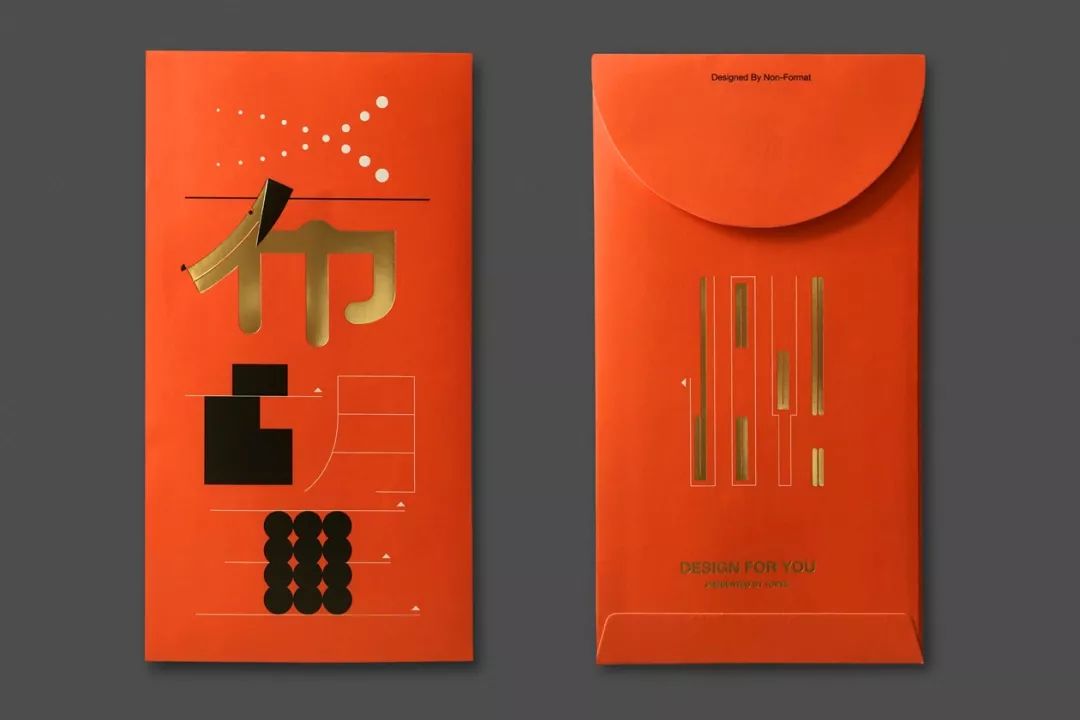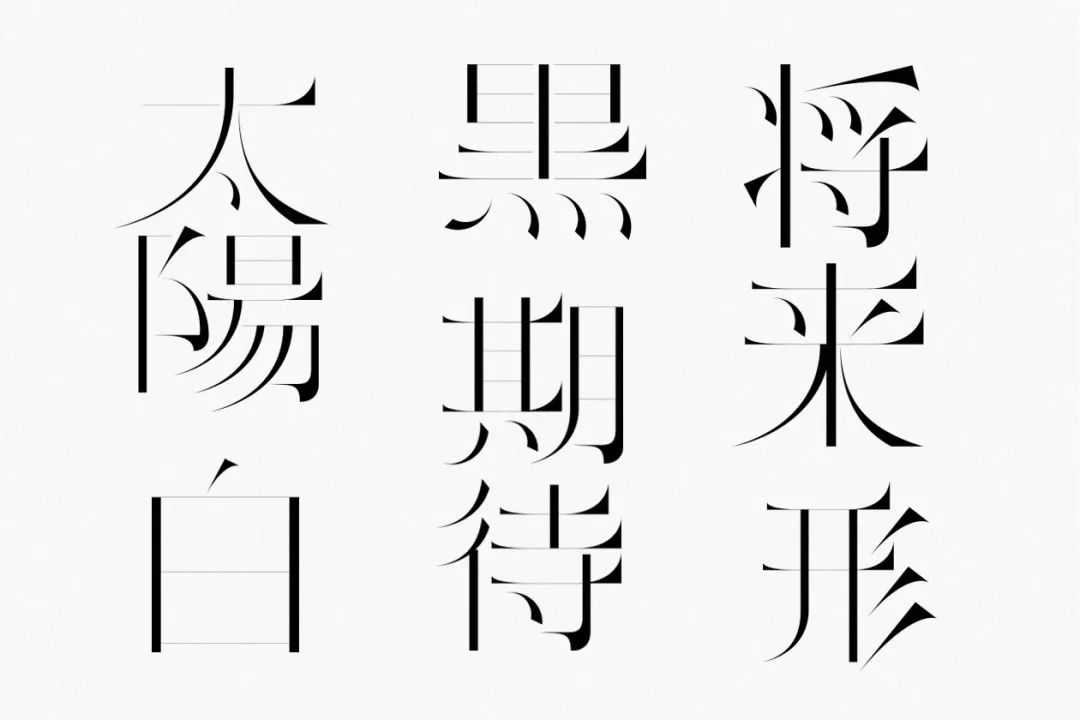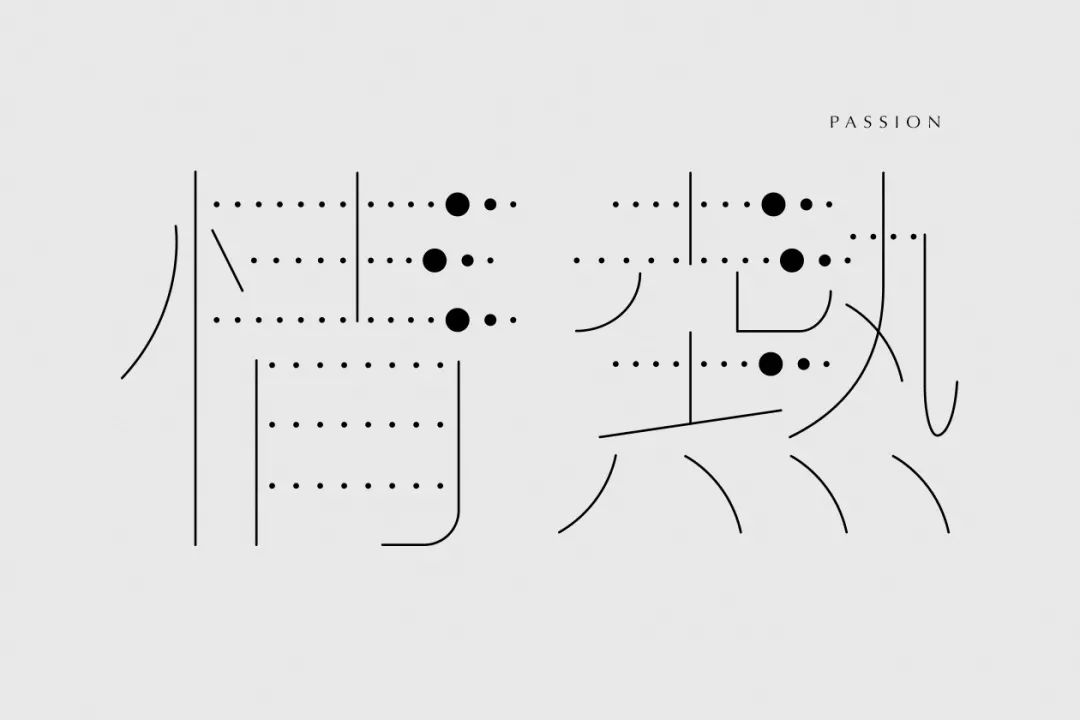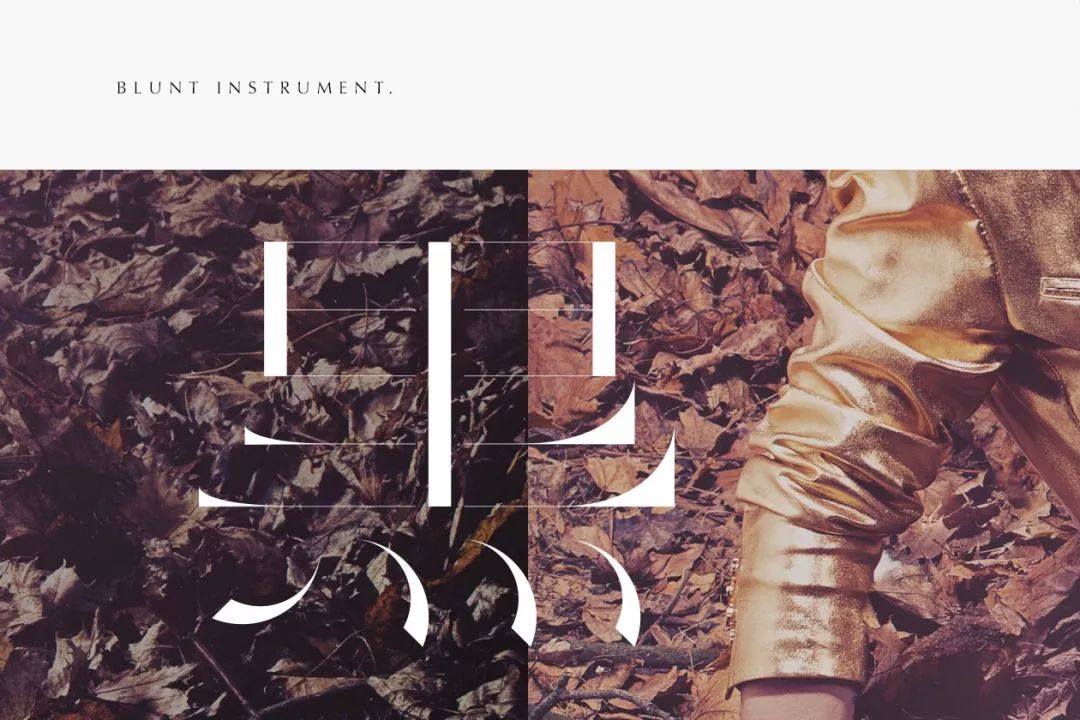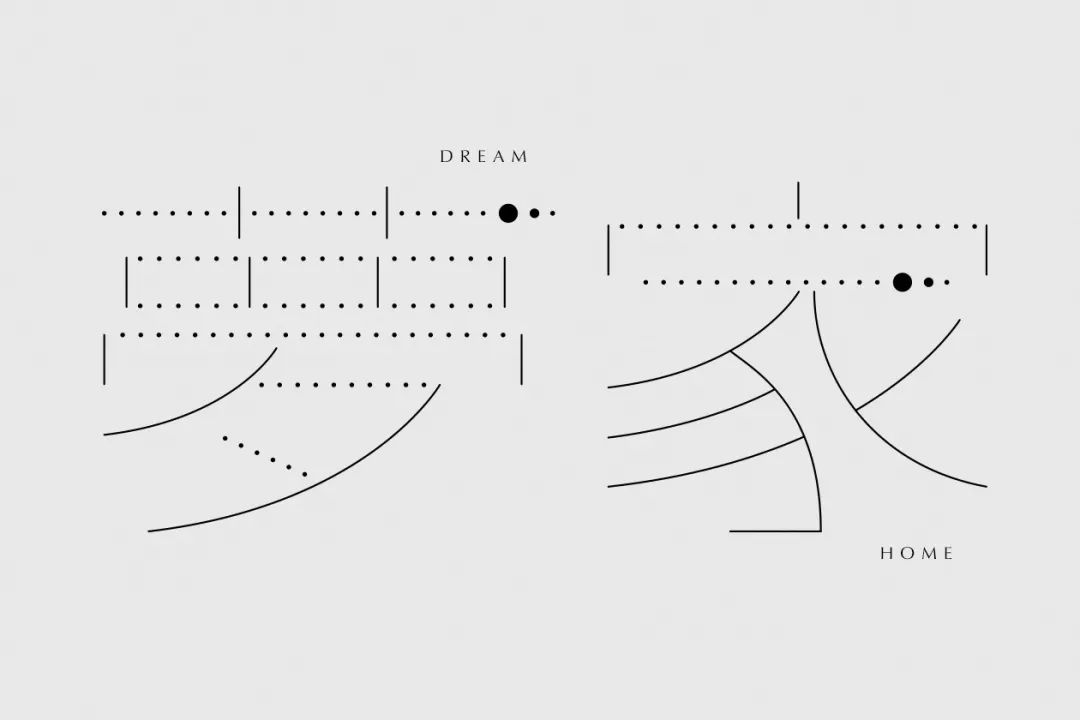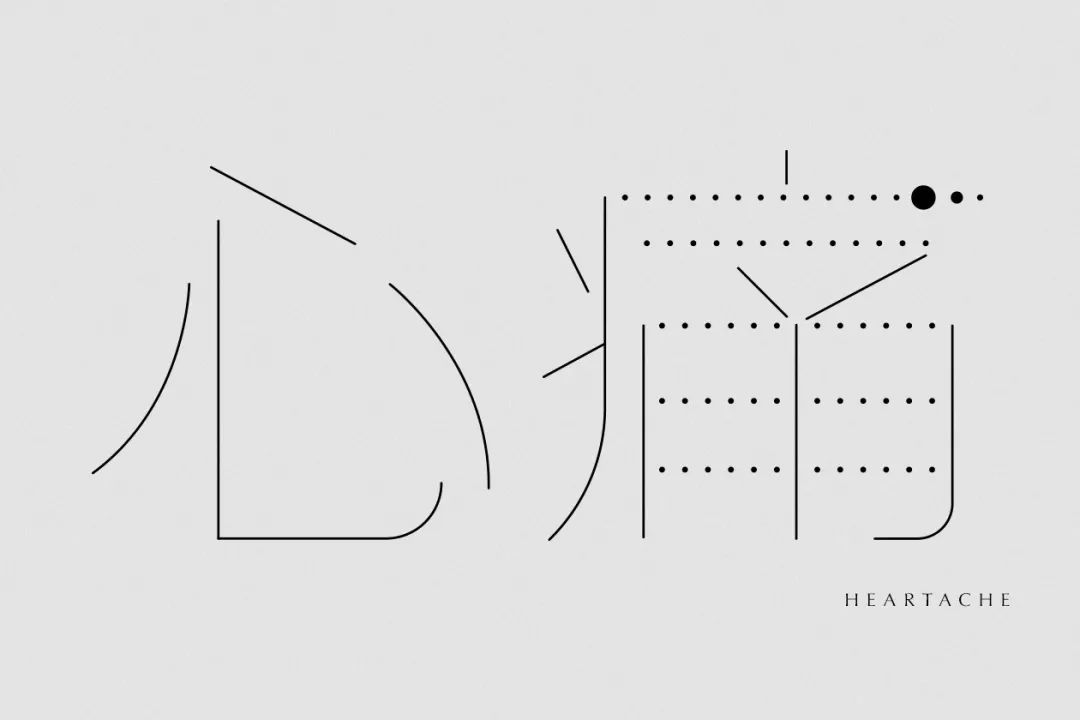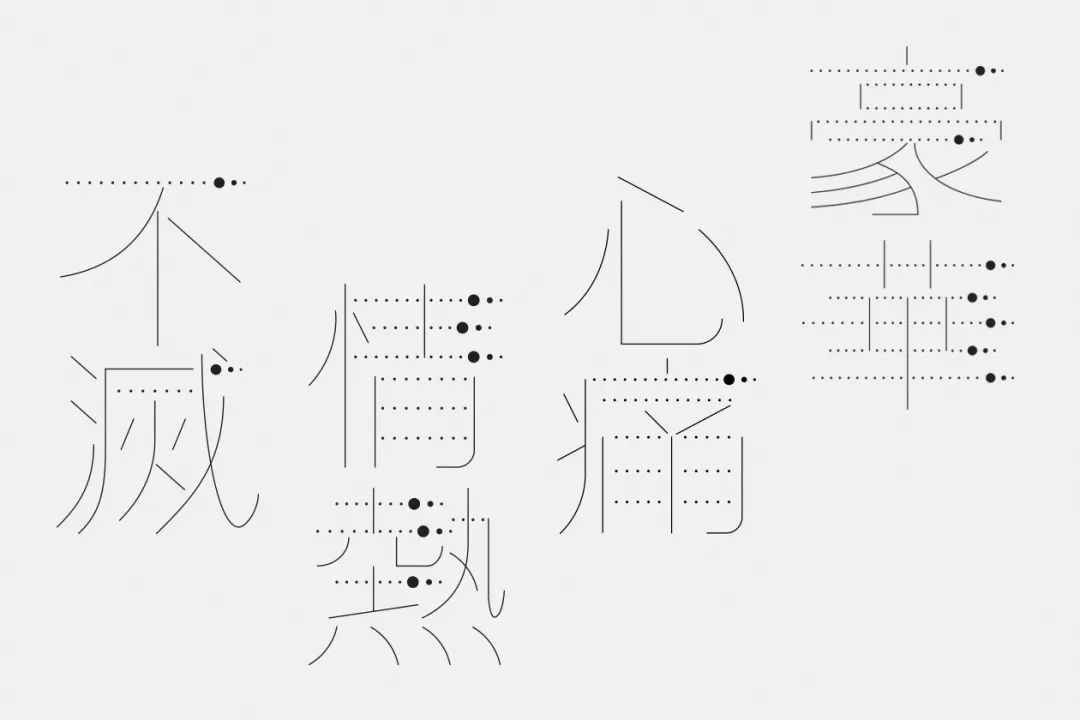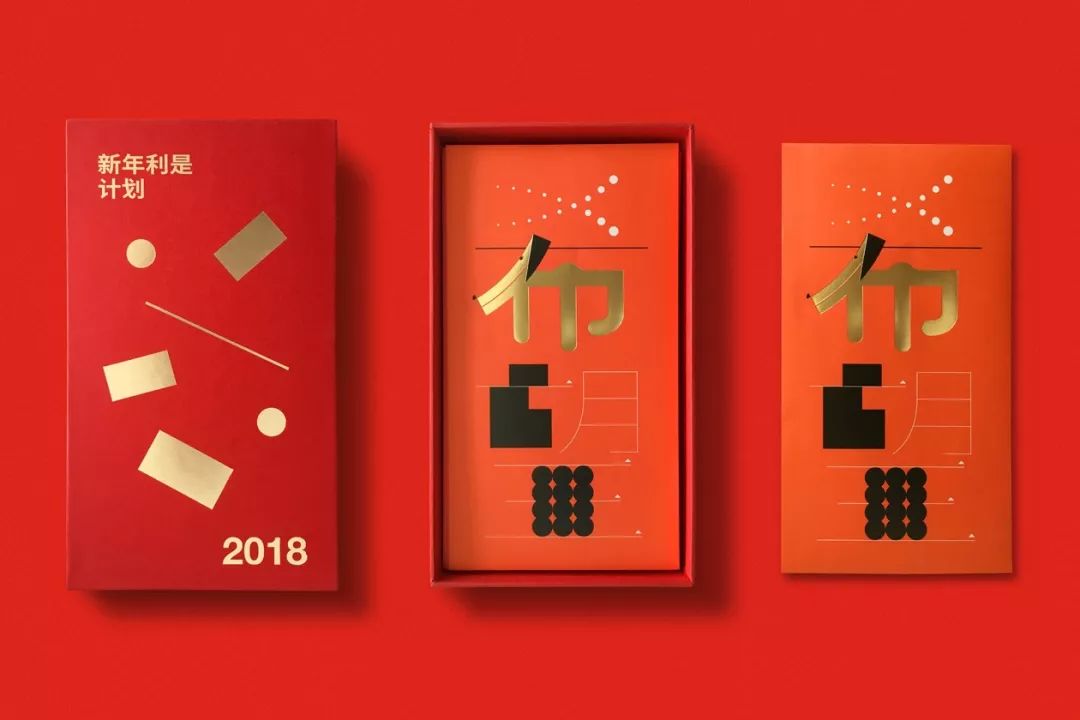
歪果仁设计的中文字体什么样?
汉字,形美如画,音美如歌,意美如诗。它简洁,高效,生动,是最先进的文字语言。
相信只要看过王磊老师的《一字一世界,一笔一乾坤》,都会被感动,王磊老师在《我是演说家》的舞台上这段汉字最美的演讲,让我们这些将书写汉字视以为常的人,顿时对汉字文化心怀感恩并心存敬畏。
现在,不仅只有每天正在使用的我们意识到汉字符号的,这几年从影视剧中,可以看到中国元素越来越受美国民众的关注和喜爱,美剧《摩登家庭》中的肩负学霸担当的二女儿Alex就提倡要学汉语,Jay鼓励Manny去挑战攀岩的时候就说,只要他干爬上去就能做任何事,Manny反问他:“是吗?我能讲中文吗?”
在西方人眼中,汉语无疑是最难的语言。不仅发音难,书写更是困难。
就连很多设计师都认为,在平面设计中,使用西文元素比使用中文元素做设计要容易。所以,当看到欧美设计师能灵活运用汉字做设计时,是件非常厉害的事。
早在2013年Non-Format设计公司就为日本Beacon Communications项目设计的日语字符。实际上就是用汉字做设计。
Non-Format是个传奇设计公司,由来自挪威的 Kjell Ekhorn 和 英国的Jon Forss创立,他们素以其富有表现力的字体设计而广为人知,除了作为西方人敢于挑战汉字设计以外,他们的工作方式也很特别,他们的两个工作室位于大西洋的两边,一个在挪威的奥斯陆,一个在美国的双子城,相差7个时区。
Kizu — Type development
Non-Format的客户类型多样,包含了各个领域的著名品牌,凭借对定制设计解决方案的坚定信念,他们一直与客户合作,帮客户定义并建立品牌。他们极具前卫的视觉风格令Non-Format赢得许多赞誉,他们的作品也受到全球各著名设计杂志的推广介绍与出版物的刊载,并曾获得了如纽约ADC金奖、英国D&AD黄铅笔、东京TDC大奖等许多奖项,作品曾收录于2017年的中国TDC (Typographic Design in China)。
Dotto — Type development
Hope & Joy — 2018年红包设计
Non-Format没有固定格式与风格的创造与追求,细看这些视觉徊异的作品,有一点可以肯定的是,他们对自己的工作充满热情,并拥有一系列令他们非常自豪的工作。每一件都可透发出Non-Format细致、追求极致与富有想像的创造力。
HOT 100 — Custom typography
Sølve typeface for S Moda — Custom typeface
Charli XCX — Custom typography
Adobe New Creatives — Infographics
Only Connect 2018 — Design for music festival
Computer Arts, issue 250 — Cover image
西方人对曾经神秘的中国元素越来越感兴趣,就连在设计界也不会例外。在未来的设计路上,我们会在国际上看到更多的中国元素运用,看到更多不同文化的碰撞、解读后产生的火花。